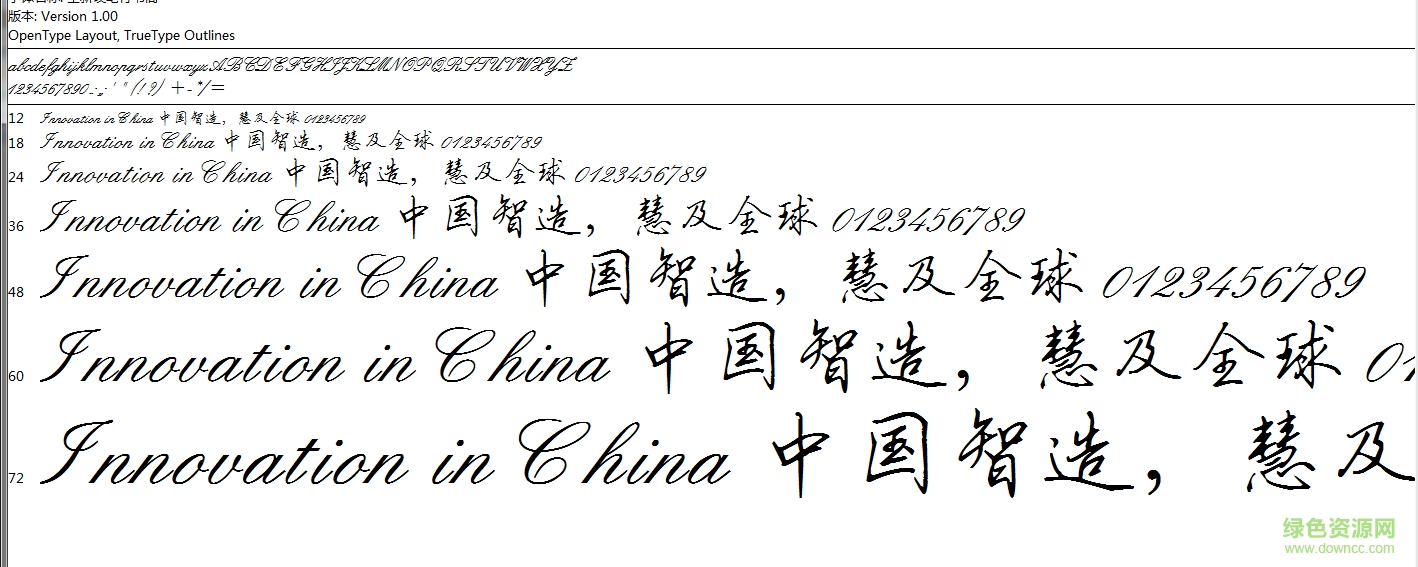
軟件介紹 軟件標簽: 鋼筆字體 字體 鋼筆行書字帖字體是網上很少見,可以作為鋼筆行書字帖的好字體,字體非常的美觀大方,非常漂亮、美觀,我們免費為您提供該字體的下載地址,歡迎您的下載使用。鋼筆行書字帖字體預覽鋼筆行書字帖字體安裝說明1、點擊打開鋼筆行書字帖字體,直接選擇安裝即可2、將字體復制到C:\Windows\Fonts文件夾即可完成安裝。注意事項本站所有字體資源僅供個人學習與參考,如需商業(yè)使用請到相關官網授權。 軟件截圖 上一張下一張(1 / 1) 安裝詳細截圖 猜你喜歡 字帖app 鋼筆行書 字帖app 字帖app可以幫助希望練字但是不方便隨時攜帶字帖的用戶進行參考哦,目前市面上的字帖app功能繁多,各種字體均具備,能夠很好地幫助用戶來掌握書法的藝術,更好進行練字!在這里小編為各位用戶帶來了幾款不錯的字帖app供大家參考下載哦! 查看更多>> 書法練字帖軟件 64.40M/中文/10.0/v2.6 安卓免費版下載 悟空練字帖 20.35M/中文/10.0/v1.1.8 安卓版下載 妙筆鋼筆字帖app 33.01MB/中文/10.0/v1.9.6 安卓版下載 鋼筆練字帖 39.69MB/中文/10.0/v1.4.7 安卓版下載 英文字帖 56.00M/中文/10.0/v1.0.0 安卓版下載 鋼筆字帖app 19.99M/中文/10.0/v1.0 安卓版下載 鋼筆行書 鋼筆行書是深受廣大用戶喜愛和青睞的一款字體,這款字體融合了鋼筆字體和行書字體的兩大精髓。既有鋼筆犀利的筆鋒,又有行書的行云流水之特色,整體效果看起來非常美觀、漂亮,有需要的朋友歡迎來綠色資源網下載使用。 查看更多>> 伯樂鋼筆行書字體 3.53M/中文/6.6/下載 李旭科鋼筆行書 4.11M/中文/10.0/下載 葉根友鋼筆行書簡體升級版 1024/中文/2.5/下載 書體坊趙九江鋼筆行書字體 1.80M/中文/10.0/下載 德彪鋼筆行書字庫 3.0 2.69M/中文/5.0/ttf版下載 龐中華鋼筆行書字帖PS版 8.59M/中文/4.7/下載 其他版本下載 標題 大小 更新日期 下載 下載地址 電腦版 鋼筆行書字帖字體 點擊報錯 軟件無法下載或下載后無法使用,請點擊報錯,謝謝! 關閉報錯反饋 請描述您所遇到的錯誤,我們將盡快予以修正,謝謝! *必填項,請輸入內容 本類最新 dreamweaver字體庫 首爾南山體字體 v1.06 官方版 潮字社風云簡ttf 潮字社凌渡鯤鵬簡體字體 潮字社曾玉波手書簡字體 微博慧心字體 相關文章 Photoshop字體安裝使用方法和技巧 如何解決“無法新增字體”問題 Win 7系統安裝字體方法 網頁字體大小設置方法 怎么改網頁字體大小 在Linux系統中安裝字體的幾種方法 windows7字體顯示問題:打開某些程序的時候顯示的是亂碼 用戶評論 熱門評論 最新評論 發(fā)表評論 查看所有評論(0) 昵稱: 請不要評論無意義或臟話,我們所有評論會有人工審核. 字數: 0/500 (您的評論需要經過審核才能顯示)